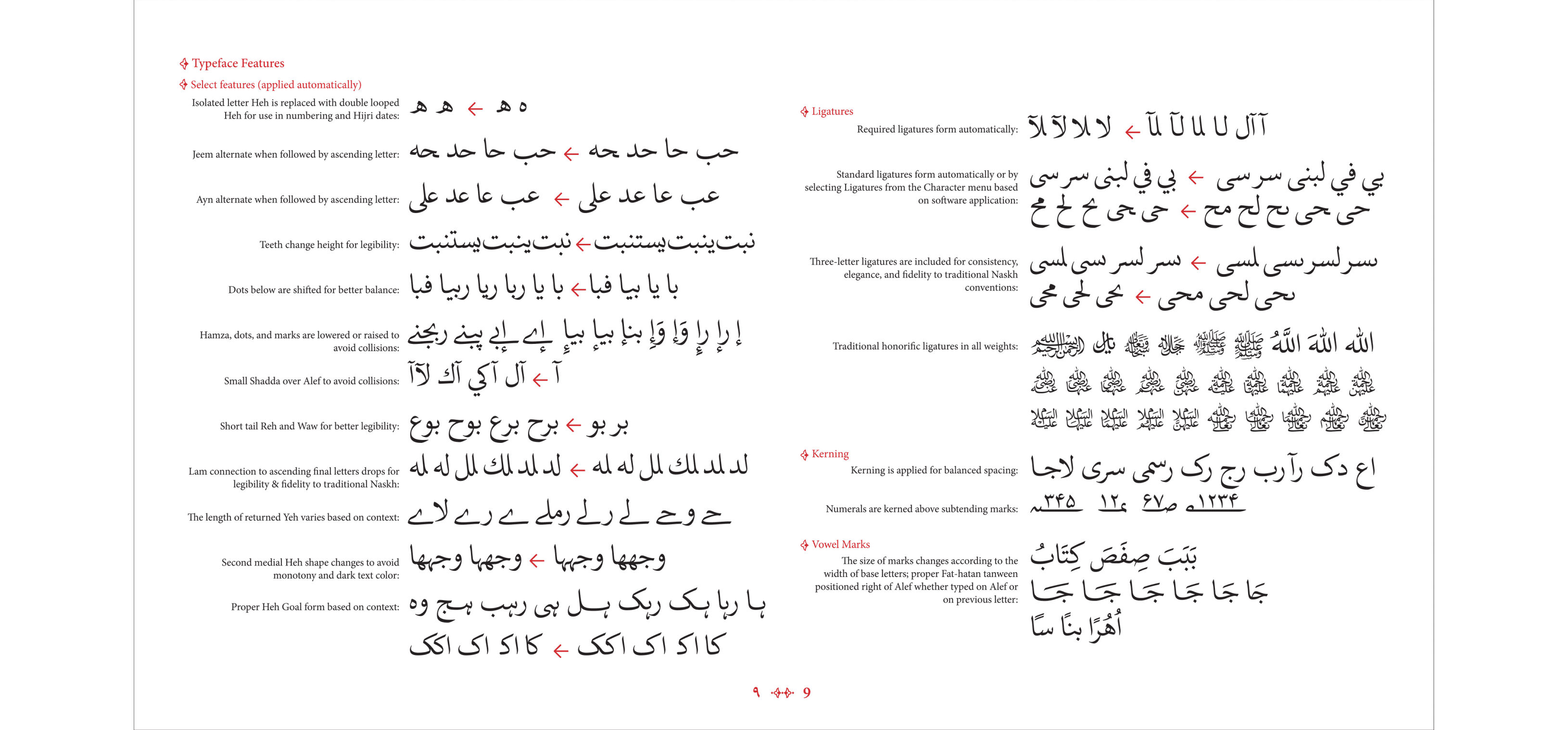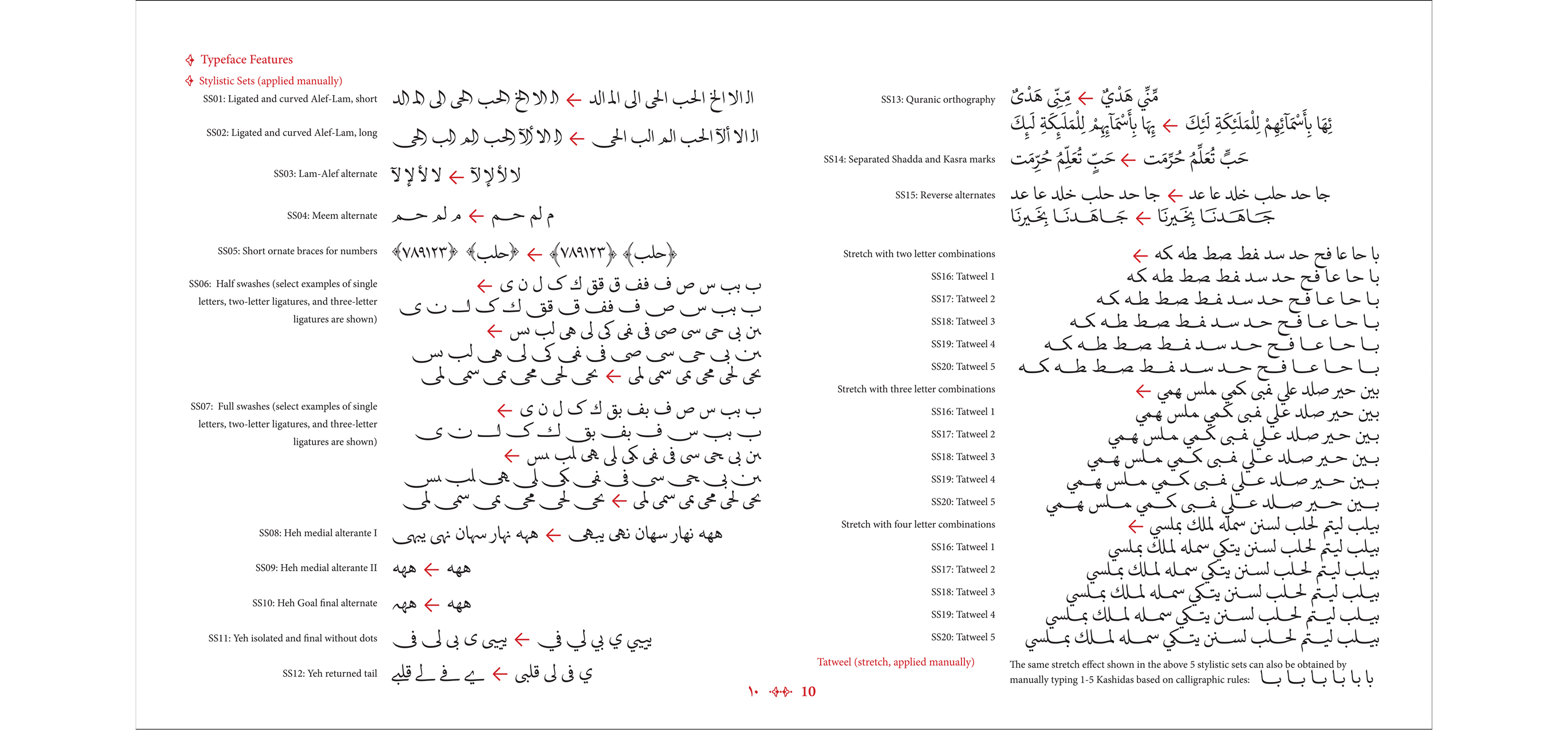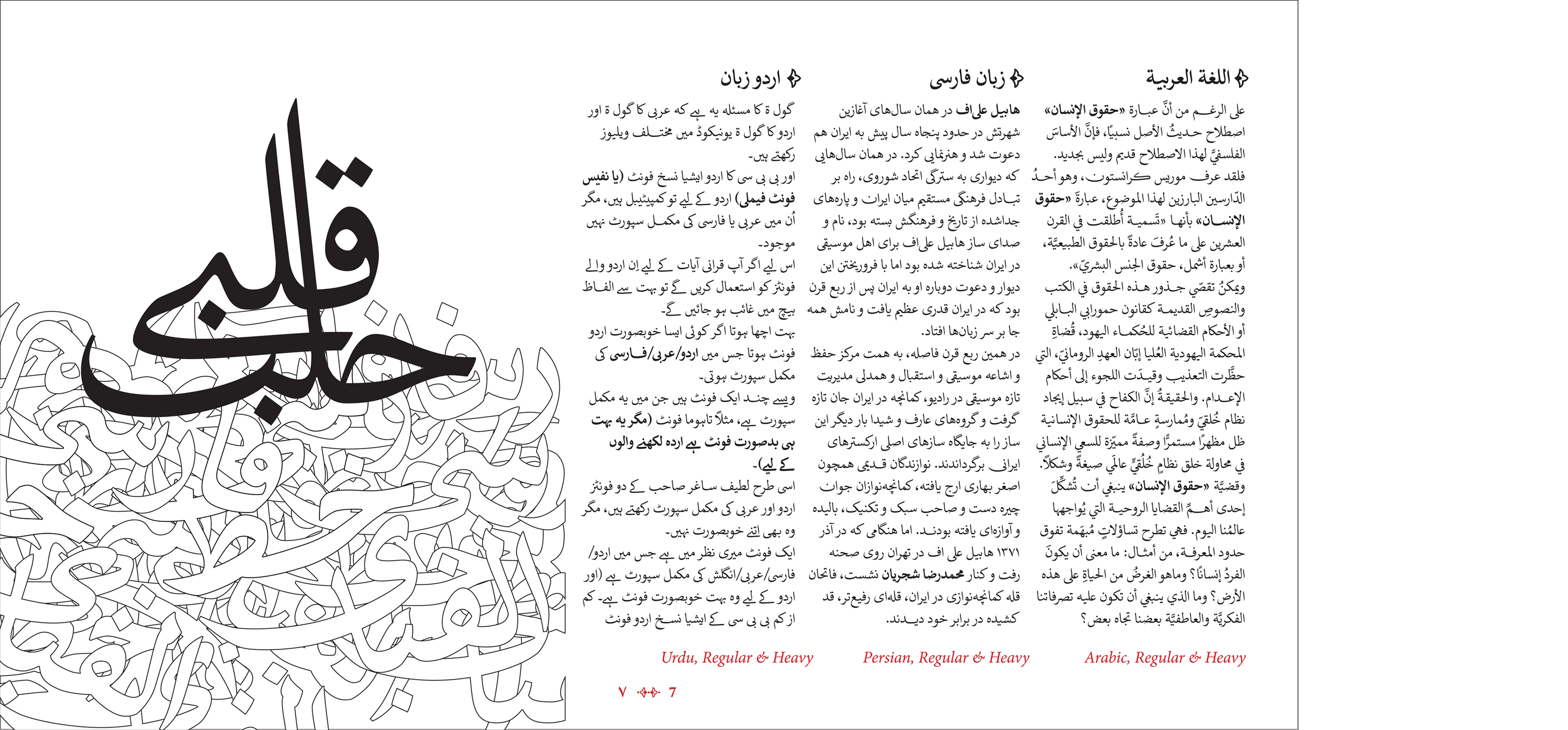
Sakkal Kitab هو خط نسخ غني بالميزات ومبني على الأسس التقليدية، مصمم خصيصًا للغات العربية والفارسية والأردية. يتميز بوضوح عالٍ في الطباعة وعلى الشاشات، مع لمسة عصرية، واتصالات خطية سلسة، وتراكيب خطية مدمجة. صُمم هذا الخط خصيصًا لضبط النصوص الطويلة مثل الكتب، ومن هنا جاءت تسميته بـ"Kitab"، أي "كتاب" بالعربية.
عائلة Sakkal Kitab تحتوي على 5 أوزان، ويقدم كل وزن 5 مستويات من الاتصالات الخطية الكاليغرافية لتحسين قابلية القراءة والمساعدة في تحقيق توازن لون النص ومحاذاة السطور. كما يتضمن عددًا كبيرًا من أشكال الحروف البديلة والتراكيب الخطية لمنح النص مظهرًا أكثر كلاسيكية وكاليغرافية. وتشمل الميزات الأخرى وضعًا دقيقًا لحركات التشكيل، مسافات بين الحروف محسّنة (kerning)، وعدة رموز تشريف تقليدية.